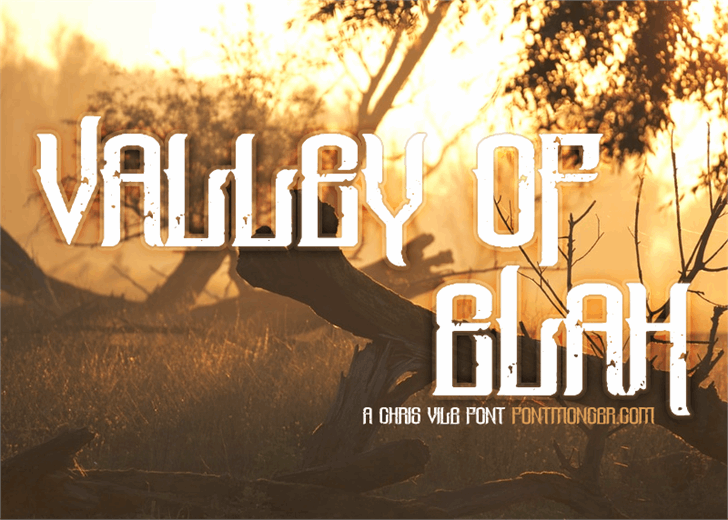
A Valley Of Elah é uma elegante fónta gótica que traz à vida textos com uma presença impressionante. Cada caractere foi cuidadosamente projetado para transmitir força e elegância, perfeitamente adaptável a diversos formatos de texto. Como parte da sua categoria exclusiva de fontes góticas, esta fónta é ideal para ambientes que buscam um estilo antiquado e arredondado. Hamilton é o designer por trás desta maravilhosa criação gráfica. A Valley Of Elah oferece uma ampla gama de opções, incluindo estilos itálico, sólido e desgastado, que permitem aos designers a flexibilidade necessária para personalizar os textos conforme necessário. Para aqueles que querem explorar ainda mais as possibilidades desta fonte, o acesso ao versão comercial é sugerida, pois ela inclui todos esses diferentes estilos. E como qualquer bom designer gráfico sabe, opções adicionais podem tornar a criação de projetos digitais um processo ainda mais gratificante e personalizável.